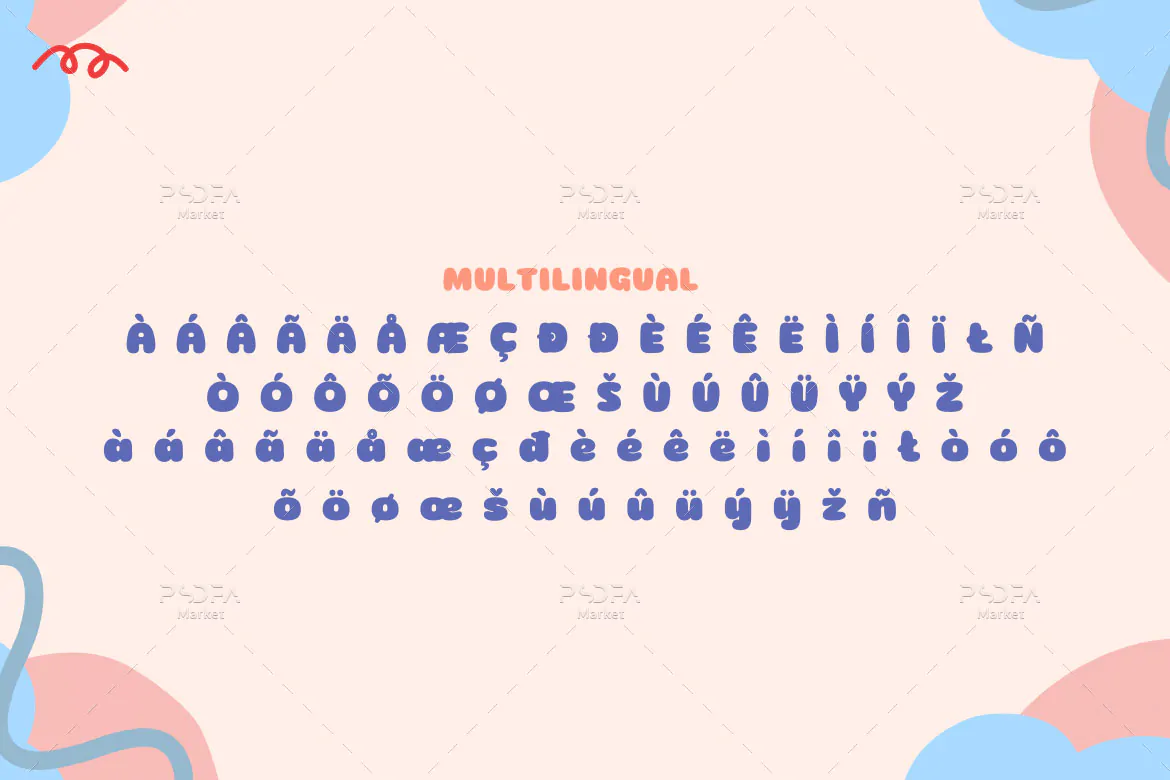
فونت کودکانه بولد و ضخیم Ginuk
فونت کودکانه بولد
فونت کودکانه بولد و ضخیم Ginuk یک قلم نمایشی و فانتزی انگلیسی است که مناسب جهت استفاده در طرح و پروژههای گرافیکی مختلف از جمله طرحهای کارتونی و کودکانه میباشد. فونت Ginuk با وزن معمولی طراحی شده است که میتوانید از آن در طراحی پوستر، بسته بندی محصولات، تقویم، لوازم التحریر و … استفاده کنید.